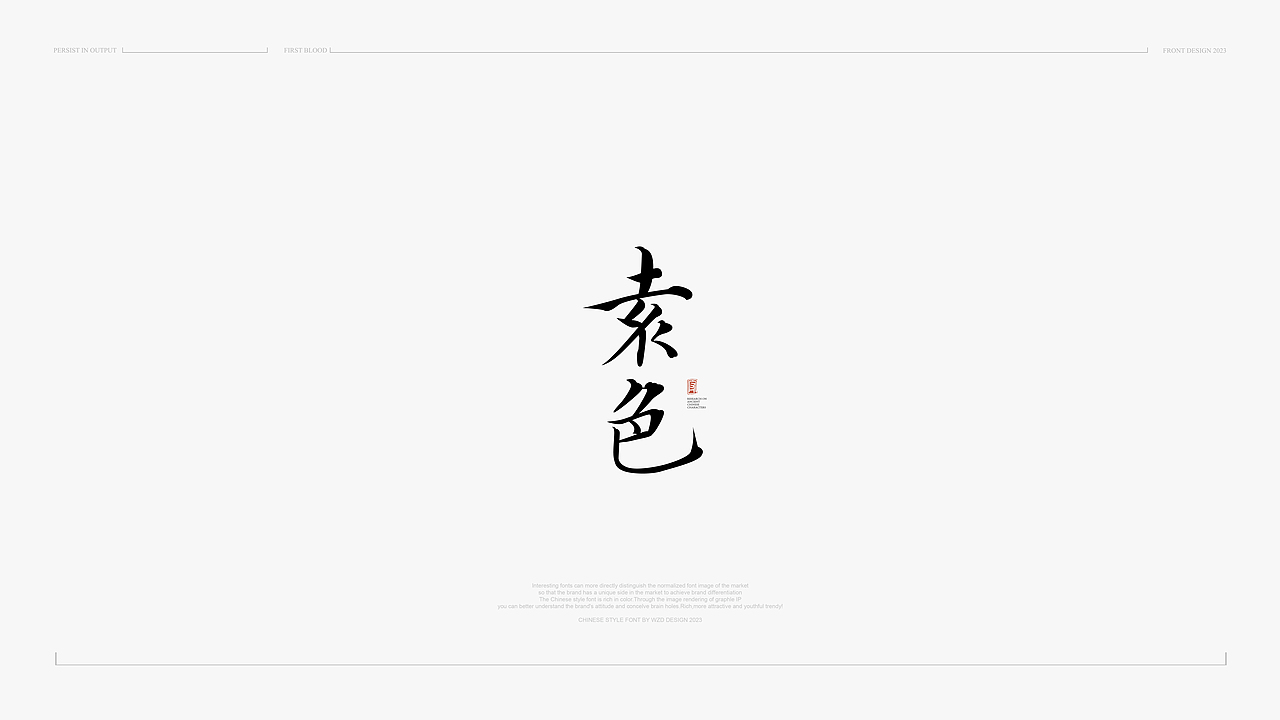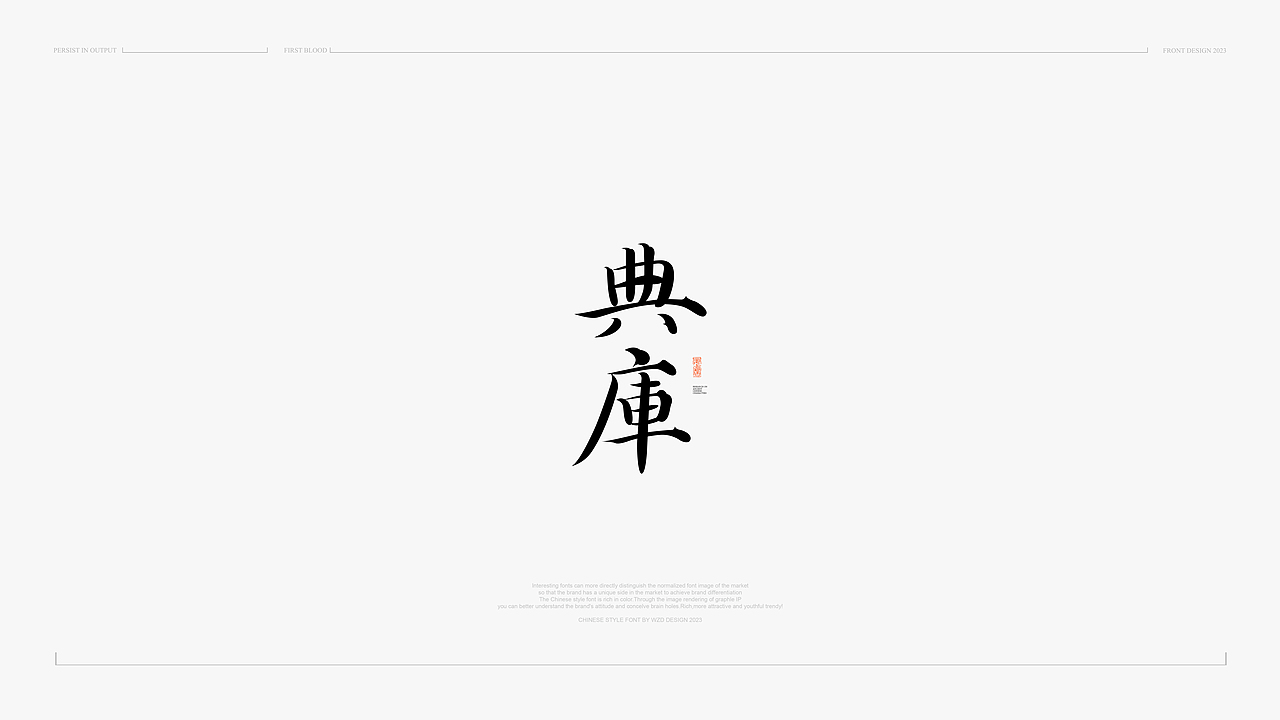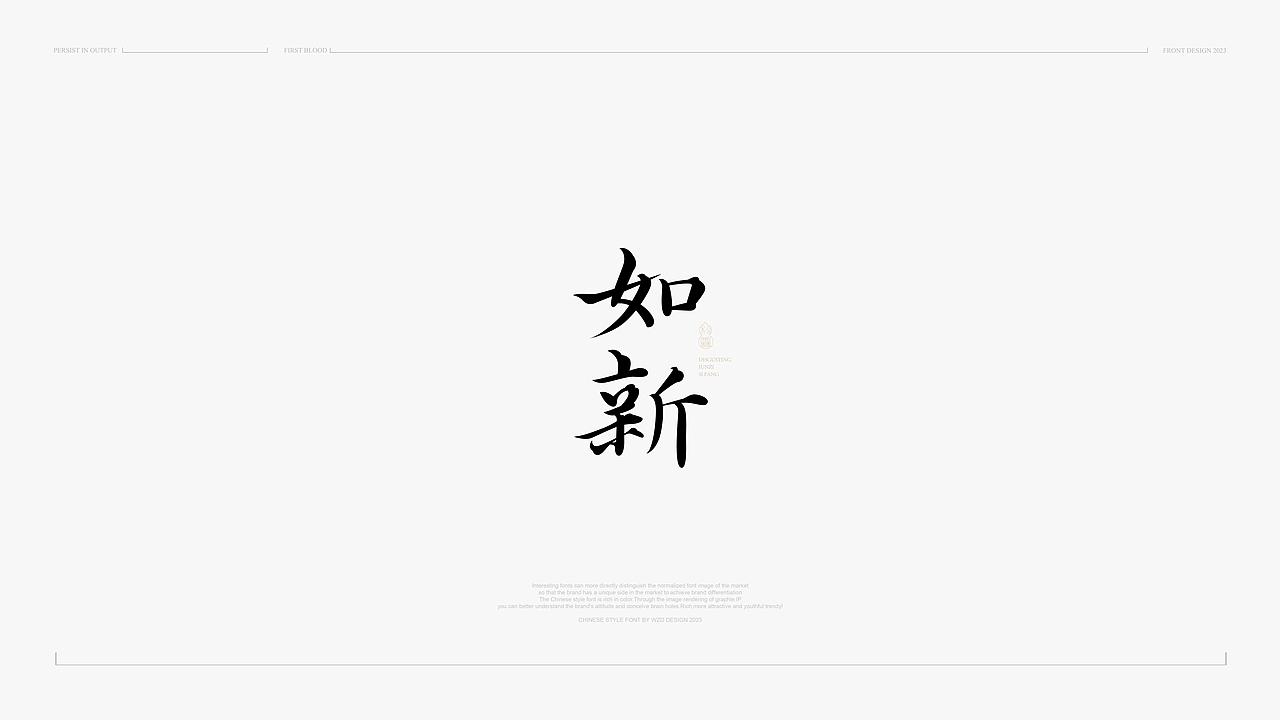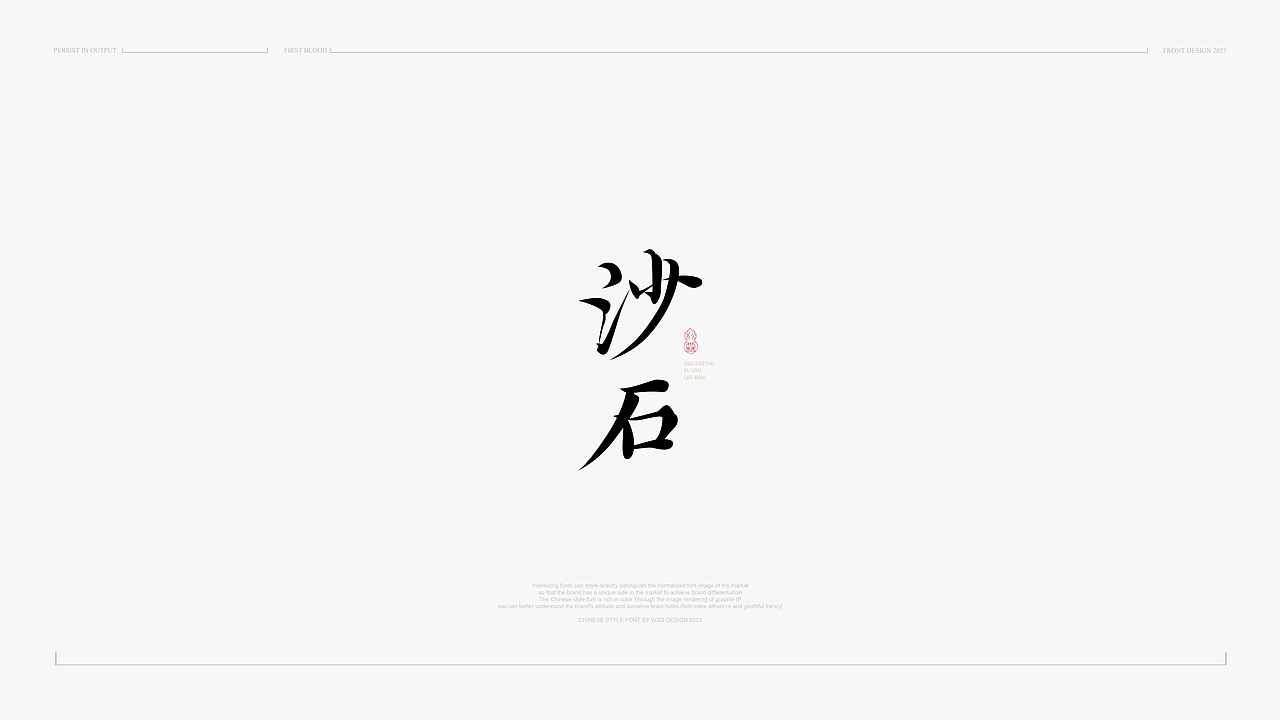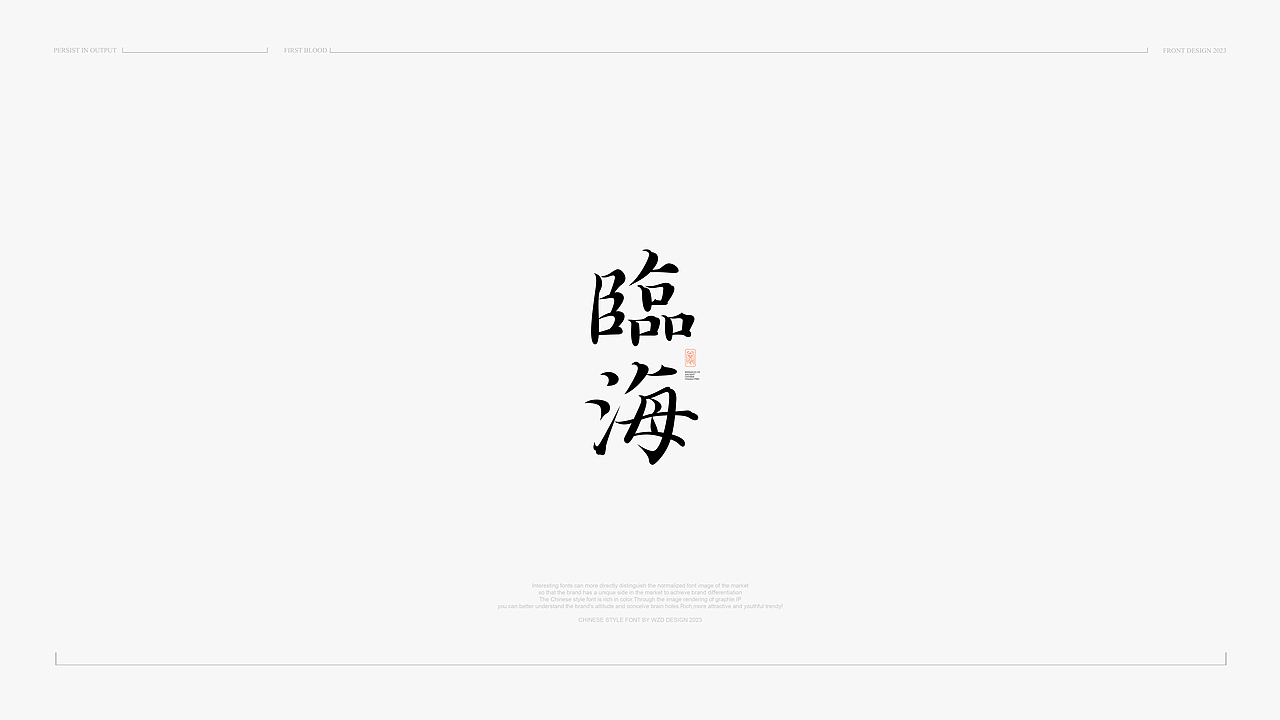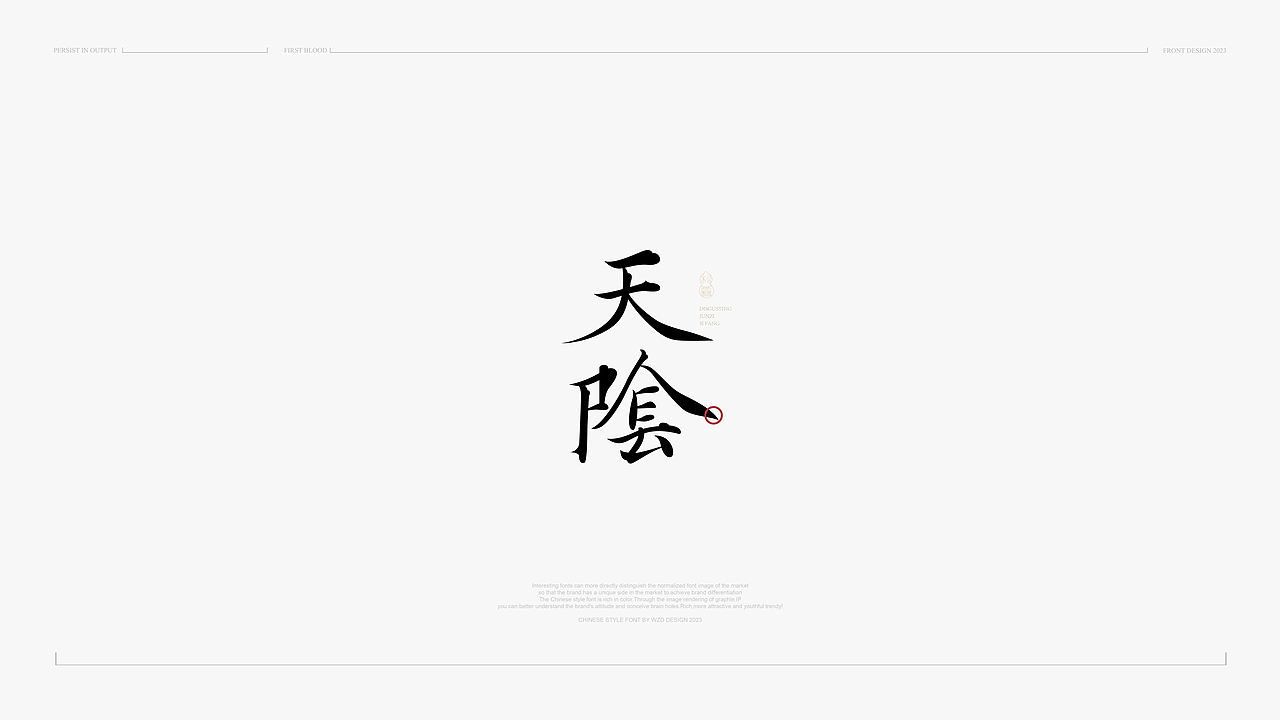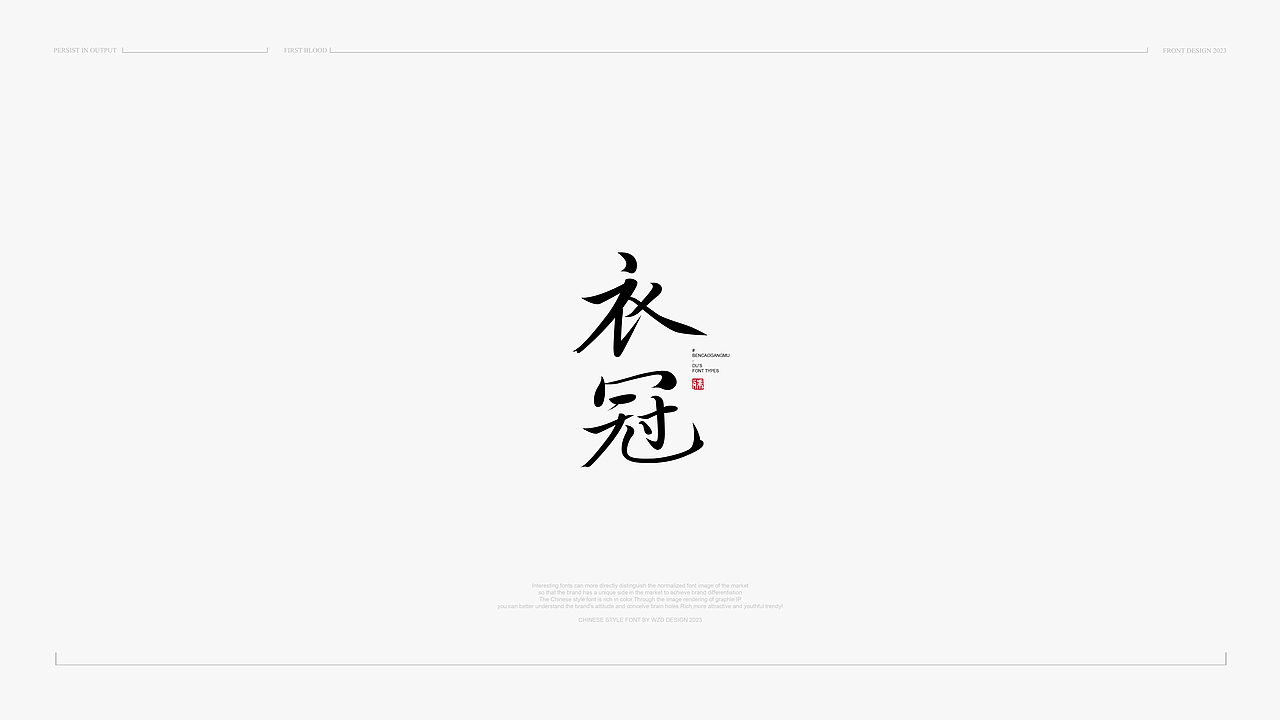
中国风&字体设计丨2023字体标志10月新篇章
项目丨PROJEC
古字新说-手写字体设计/2023.10.10
古风字体/字体设计
质胜文则野,文胜质侧史。文质彬彬,然后君子。
The quality is better than the text, and the quality of the literature is on the side of history. Be gentle, and then a gentleman.